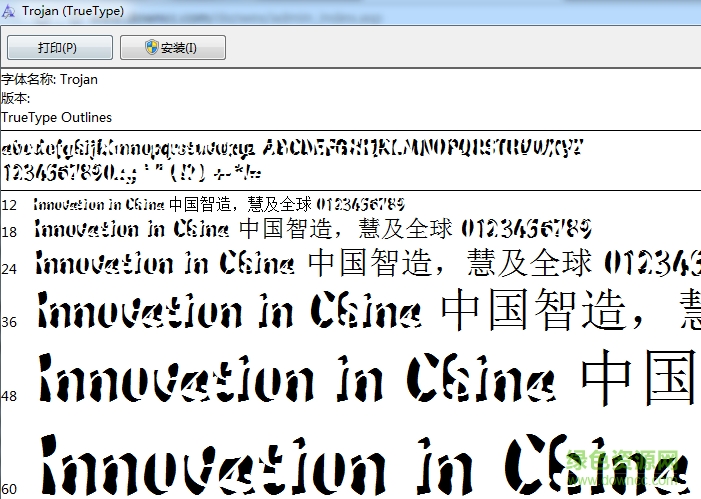
TROJAN字體是英文字體庫(kù)中的個(gè)性字體,該字體擁有超多精彩的線條,讓用戶能夠享受個(gè)性字體帶來(lái)的特性,有喜歡的朋友就來(lái)綠色資源網(wǎng)下載使用吧!
TROJAN字體是一款個(gè)性英文字體,字體的字型十分出色,給人一種過(guò)目難忘的感覺(jué),有需要的朋友就趕快來(lái)綠色資源網(wǎng)下載吧!